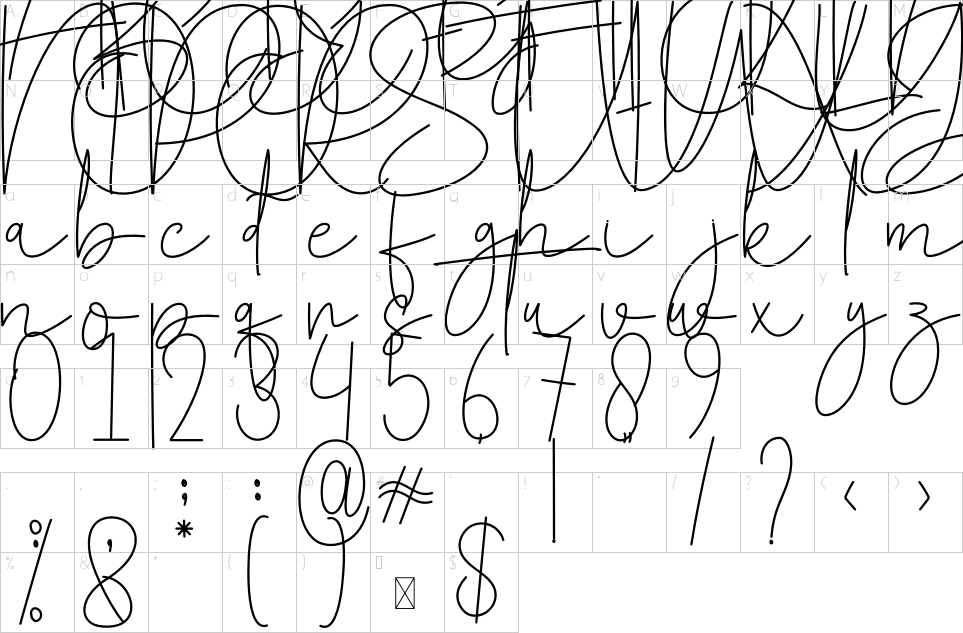
A Santaclause Font oferece um toque de magia e encanto para qualquer projeto. Desenhada por William Jhordy, esta fonte é ideal para personalizar presentes de natal, decorações ou até mesmo adicionar um toque criativo a sua identidade visual de negócios durante o mês do Natal. Com seu design cuidadosamente elaborado, esta fonte adicional de 1001 Free Fonts deixa seu projeto com um toque especial, capaz de capturar a magia do período de Natal. Recentemente baixada 421 vezes, a Santaclause Font é uma excelente opção para quem busca um toque único e encantador sem precisar gastar. Sem dúvidas, ela é uma excelente adição para qualquer designer gráfico.